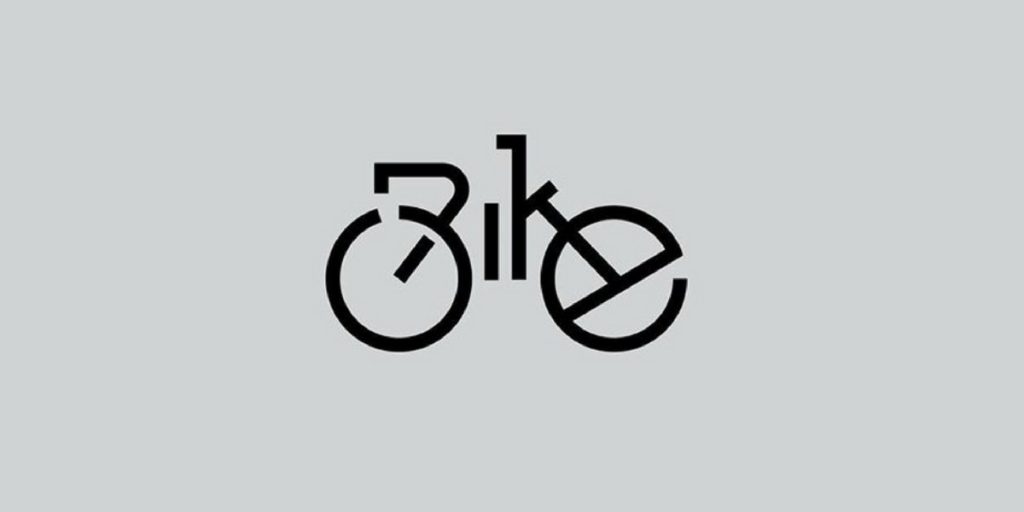
Nerdig by Nature: Designer entwirft jeden Tag ein neues Typografie-Logo
Viele von uns können nur unter Druck produktiv sein. Um sich selbst zum Abliefern zu motivieren soll es ja laut jedem Productvity-Ratgeber angeblich hilfreich sein, sich selbst Deadlines zu setzen. Der schwedische Grafikdesigner Daniel Carlmatz hat vielleicht einen Ratgeber zu viel gelesen, denn er hat sich nicht nur eine einzige Deadline gesetzt, sondern gleich 365. Für seine Wordplay Challenge nahm er sich 2017 vor, jeden Tag ein neues Logo zu entwerfen. Der Twist: Jedes der typografischen Logos muss eine Verbindung zur Bedeutung des Wortes ziehen. Das „J“ in „Jazz“ hat darum die Form eines Saxophons und das „a“ in „search“ sieht aus wie die Search Bar einer Suchmaschine. Die Ergebnisse veröffentlichte er auf seinem Instagram-Account: